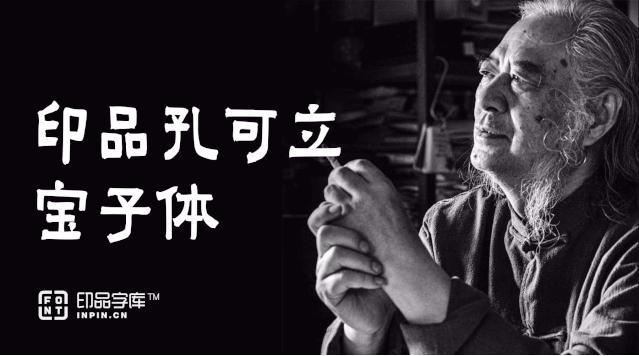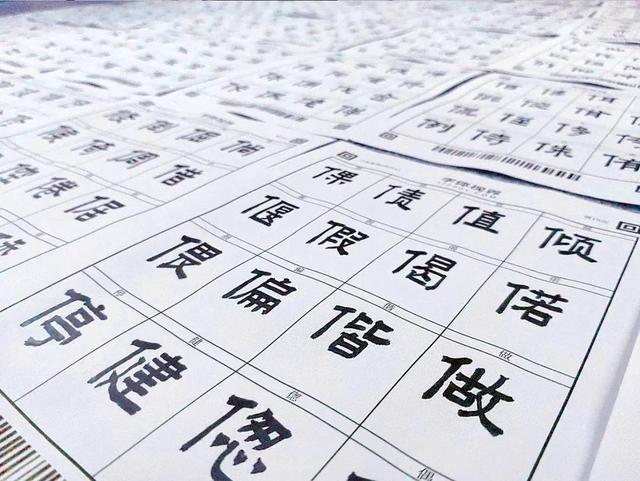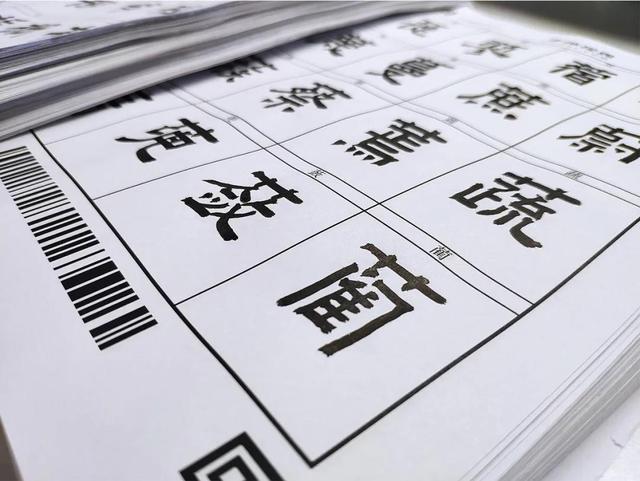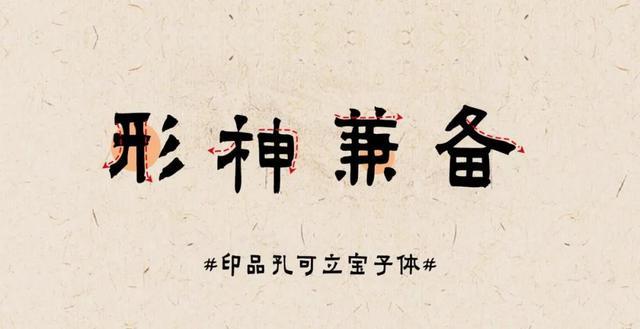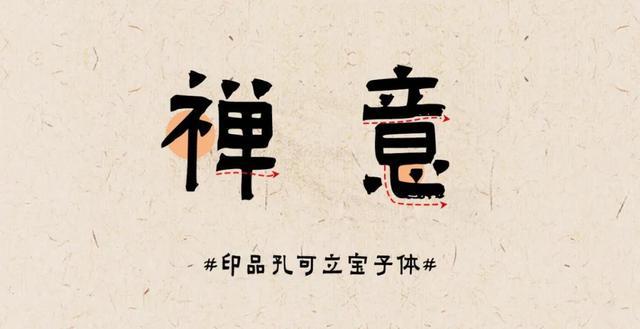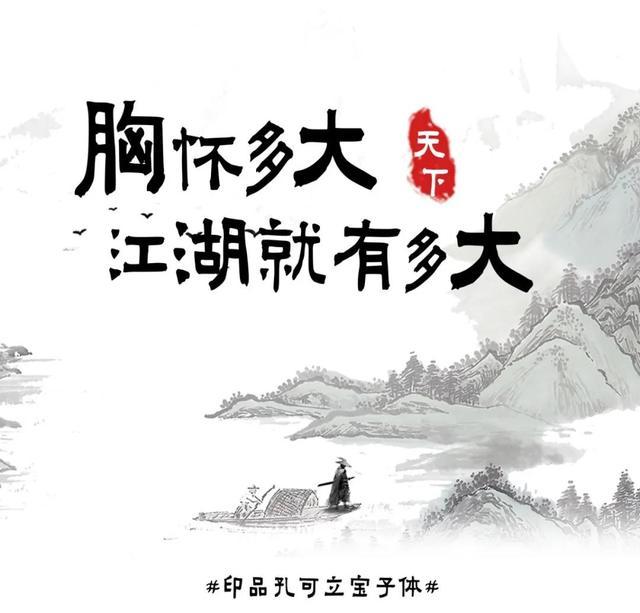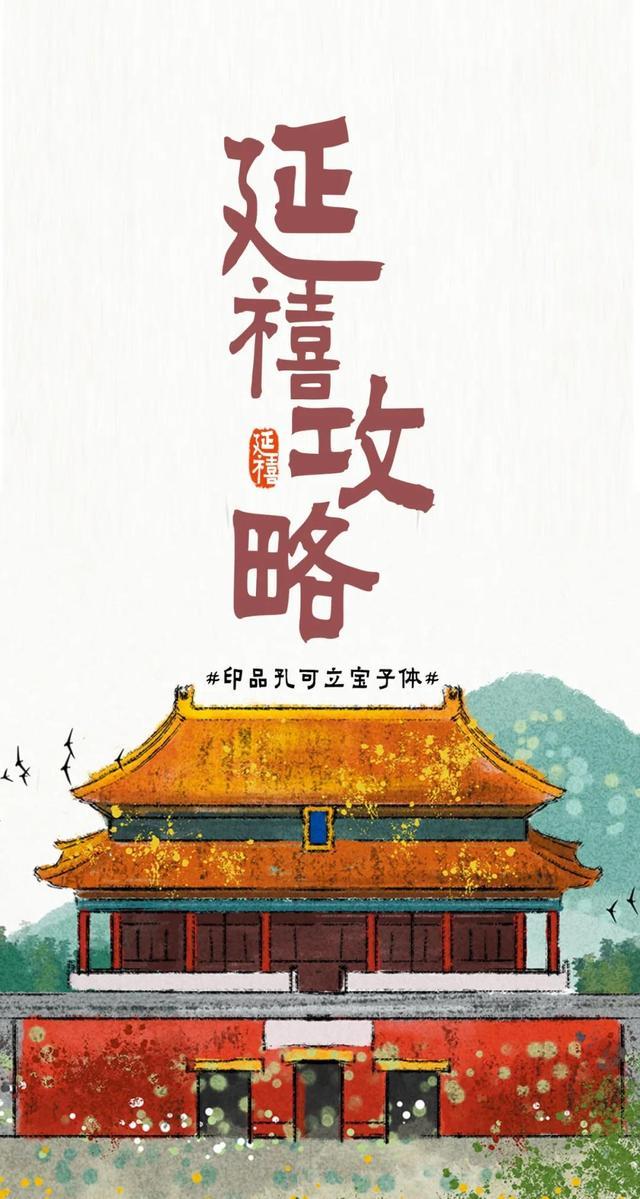
字体视界旗下印品字库携手孔子后裔孔可立推出
中国汉字字体是人类文明的活化石,书法是中华文明史上的璀璨瑰宝,是所有中华儿女的精神财富,在数千年历史中承传应用焕发着不朽的生命力。是字体创作取之不尽用之不竭的源泉。
作为深受儒家文化影响的孔圣后代,孔可立先生自信、自强、自修、自尊、自省,入世而不媚俗,心境平和但始终炙热,几十载如一日致力于对书法传统的传承、突破与创新。
孔可立宝子体是孔可立先生积五十年爨宝子碑临池心得,辅以张迁碑,爨龙颜碑,嵩髙灵庙碑等笔意而卓然形成个性鲜明的纯方笔楷书,具备典型的艺术生命力!宝子体是汉代隶书渐变为楷书的唯一存世而方笔用笔古朴奇拙的优秀书法艺术作品!
印品孔可立宝子体通过一笔一画的打磨,体现了宝子体的端庄、典雅、从容与细腻。而孔可立先生书法功力深厚,法度 严谨,高古典雅,苍利隽秀,动静相生,形神兼备,个性鲜明,独步一蹊及对文化传承的决心,也在字体细节和气质神韵中得以彰显。